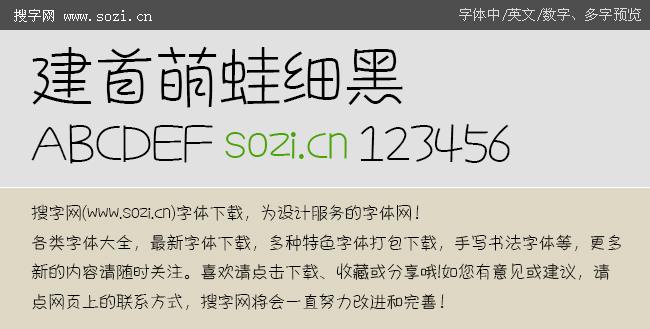
建首萌蛙細(xì)黑
搜字網(wǎng)提供一款建首萌蛙細(xì)黑中文字體下載,建首萌蛙細(xì)黑是一套卡通風(fēng)格的POP字體。字體筆畫簡潔醒目,字形為卡通風(fēng)格,充滿童趣,看上去非?蓯。適合兒童包裝設(shè)計(jì)、海報(bào)設(shè)計(jì)、廣告設(shè)計(jì)等應(yīng)用。